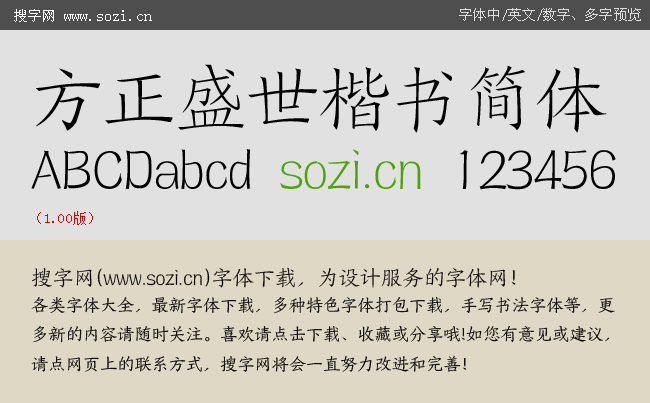
方正盛世楷書簡體
搜字網(wǎng)給大家提供一款方正盛世楷書簡體中文書法字體下載。盛世楷書風(fēng)格硬朗,與傳統(tǒng)楷書相比,字谷寬闊許多。其行筆流利,起收分明,筆筆堅實又富彈性。注重精氣神在書法藝術(shù)中的灌輸,一改傳統(tǒng)楷書精神面貌,給人充滿朝氣之感,帶給讀者一種全新的視覺體驗?捎卯媰栽O(shè)計、平面設(shè)計、印刷包裝、報紙雜志等廣告設(shè)計場合使用。